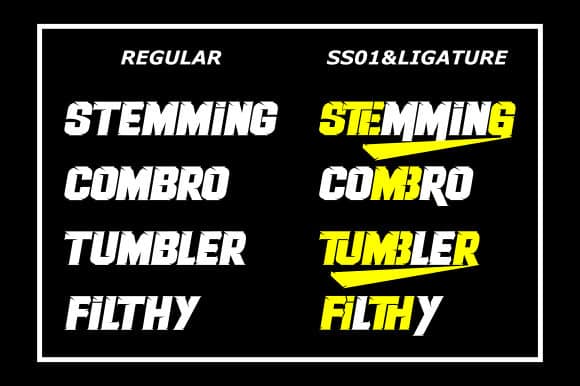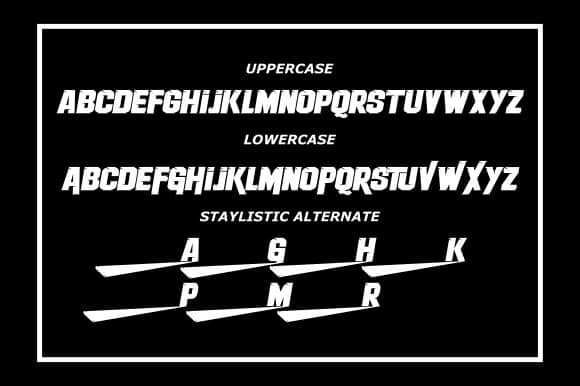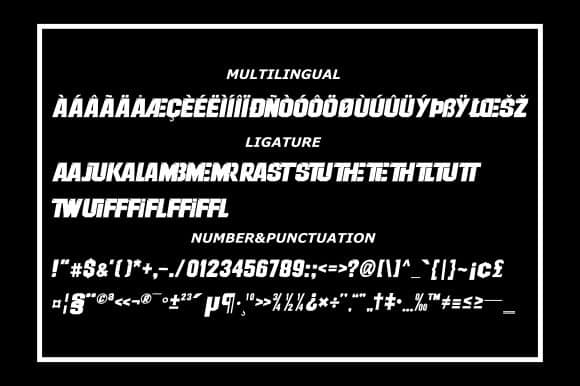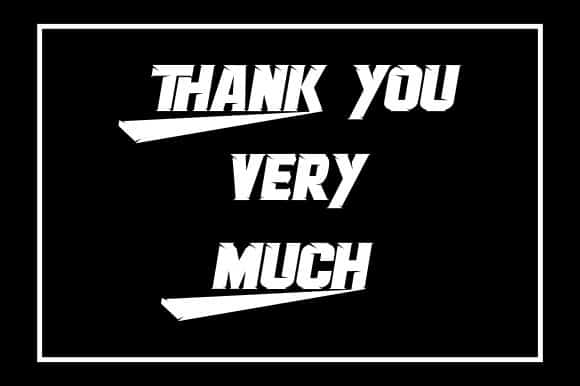
Therace Display Font
Font Tampilan Therace , namun canggih dan menampilkan karakter tebal dan panjang yang akan terlihat sangat mahir saat digunakan dalam logo, branding, desain kemasan, dan banyak lagi. Font tampilan yang dirancang dengan ahli ini benar-benar harus dimiliki.